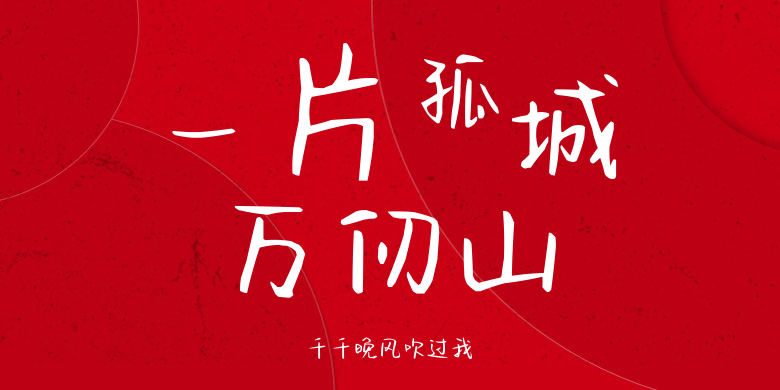
千千晚风吹过我
千千晚风吹过我,这款字体结构工整、笔画清晰,兼顾美观与易读性,适用于标题、正文、海报、包装、LOGO 等多种场景。字形优雅稳定,风格百搭耐看,适配日常排版与创意设计,让文字呈现更舒适、更具质感。千千晚风吹过我一笔一画,皆是细节,以均衡的比例、流畅的线条打造舒适视觉体验,字形端正大气,风格简约现代。无论是商业设计、品牌宣传还是日常排版,都能轻松驾驭,让文字更有格调与力量。千千晚风吹过我字体下载。